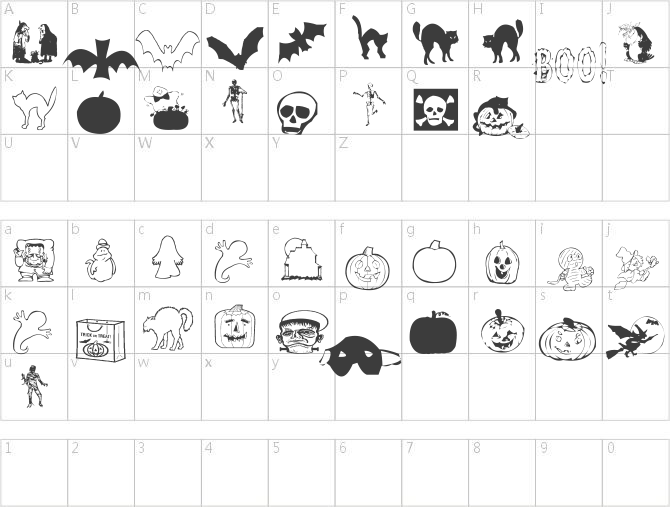
aez halloween dingbats 詳情頁
aez halloween dingbats
aez halloween dingbats字體字庫是一款讓人賞心悅目、百看不厭的英文字體,適合各類廣告和產品包裝設計應用,字體大小0.12MB,格式為ttf字體,上傳用戶是趙家玉,作者/版權方為未知